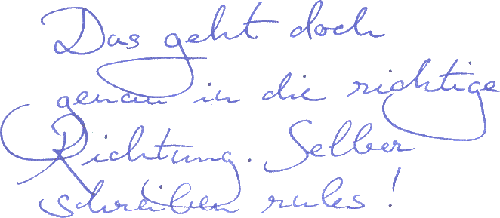
magrittes handschrift
seine handschrift gibts auch als type, weiß jemand wie sie heißt?
alle, die so ähnlich aussehen, suche ich auch...bis jetzt vergeblich.
hm danke, auch schön, aber die wirkt irgendwie nicht so naiv wie ich es gern hätte
genau, die sind auch gut! sehr gut sogar, juhu :)
aber irgendwie sind die dann wieder nicht so verspielt, oje.. in alten französischen und auch deutschen filmen kommen diese schriftarten, die ich haben will, öfter vor.
sie sind schon sehr schulschreibstil-like, aber ein bisschen ungebändigter und verschnörkelter auch
"Dies ist keine Pfeife" steht auf Magrittes Original.
aach, die wirken auf mich jetzt wieder zu erwachsen :?
ich brauch da eher was süßes, nicht so auf schön, eher auf lieb und kindlich, aber nicht kitschig, sowas:
ich denke mit den schulschriftarten komm ich eh ganz nah ran, ansonsten muss ich halt echt versuchen diese schrift mit der hand zu imitieren. danke für eure hilfe so far :)
"Dies ist keine Pfeife" steht auf Magrittes Original.
"Dies ist eine Pfeife" hat unsere Tochter daraus gemacht.
hat deine tochter die schrift mit hand nachgemacht oder fotokopiert?
Abgemalt. Für Schriften hat sie ein Händchen. Aber ich muß zugeben, daß ich da als Vater ein ganz Klitzkleinwenig voreingenommen urteile.
Vielleicht die Handsome von Nick Shinn (bei FontShop)